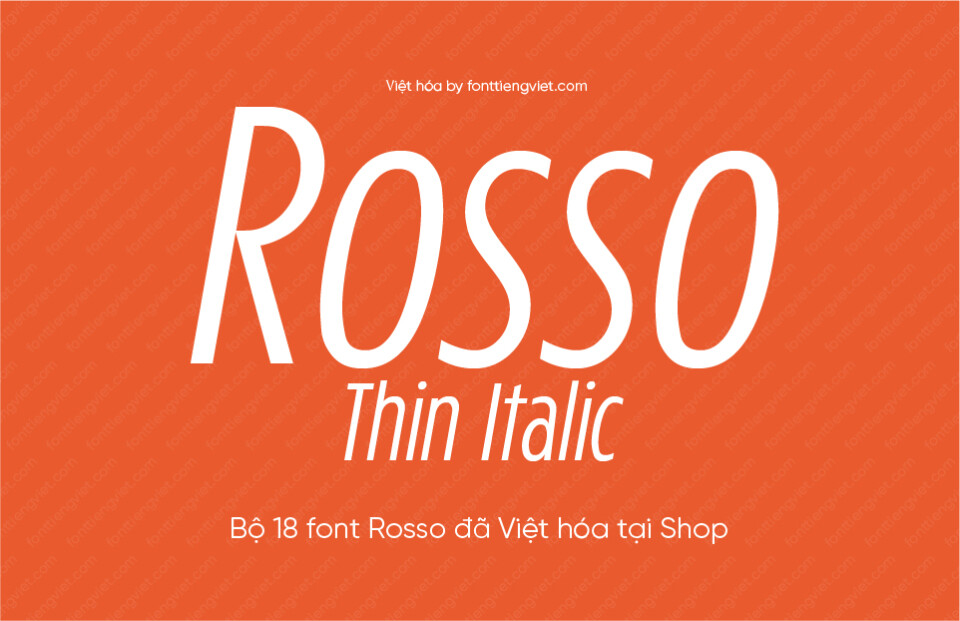
Font Việt hóa 1FTV VIP Rosso Thin Italic
Giới thiệu về bộ Font Việt hóa 1FTV VIP Rosso Thin Italic
Trong thế giới đồ họa hiện đại, việc lựa chọn một bộ Font Việt hóa 1FTV VIP Rosso Thin Italic phù hợp đóng vai trò quyết định đến linh hồn của tác phẩm. Đây là một phông chữ thuộc phong cách hiện đại với những đường nét thanh mảnh, tinh tế và đầy sự quyến rũ. Nếu bạn đang tìm kiếm một Font Miễn Phí để làm mới các dự án sáng tạo của mình, thì đây chính là lựa chọn không thể bỏ qua. Phiên bản Italic (nghiêng) mang lại cảm giác chuyển động nhẹ nhàng, giúp văn bản trở nên uyển chuyển và có chiều sâu hơn so với các định dạng thông thường.
Đặc điểm nổi bật của kiểu chữ Rosso Thin Italic
Đúng như tên gọi, 1FTV VIP Rosso Thin Italic sở hữu độ dày nét cực kỳ mỏng (thin), tạo nên sự thanh thoát tuyệt đối. Các ký tự được thiết kế với cấu trúc hình học chuẩn mực nhưng vẫn giữ được nét mềm mại nhờ các đường cong được xử lý khéo léo. Khi được Việt hóa bởi đội ngũ chuyên nghiệp, phông chữ này hỗ trợ đầy đủ hệ thống dấu tiếng Việt mà không bị lỗi hiển thị hay mất chân, giúp các nhà thiết kế tại Việt Nam yên tâm sử dụng trong các bài thuyết trình, ấn phẩm trường học hoặc trang trí báo tường kỹ thuật số.
Ứng dụng thực tế của Font Việt hóa 1FTV VIP Rosso Thin Italic
Nhờ vào vẻ ngoài sang trọng và đẳng cấp, bộ phông chữ này thường xuyên xuất hiện trong các lĩnh vực đòi hỏi tính thẩm mỹ cao. Bạn có thể sử dụng nó để thiết kế tiêu đề cho các tạp chí thời trang, bìa sách nghệ thuật hoặc thiệp mời sự kiện. Trong môi trường giáo dục, giáo viên và học sinh có thể dùng phông chữ này để làm nổi bật các câu trích dẫn hay trong slide bài giảng, tạo nên một không gian học tập đầy cảm hứng và hiện đại.
Lưu ý khi phối hợp font chữ trong trình bày
Mặc dù Font Việt hóa 1FTV VIP Rosso Thin Italic rất đẹp, nhưng do đặc tính nét mảnh, bạn nên sử dụng nó ở kích thước lớn để đảm bảo khả năng đọc tốt nhất. Tránh dùng phông chữ này cho các đoạn văn bản dài (body text) vì có thể gây mỏi mắt. Thay vào đó, hãy kết hợp nó với các phông chữ không chân (Sans-serif) có độ dày trung bình để tạo ra sự tương phản thị giác mạnh mẽ, giúp bố cục thiết kế trở nên chuyên nghiệp và hài hòa hơn bao giờ hết.
Lời kết về bộ chữ 1FTV VIP Rosso Thin Italic